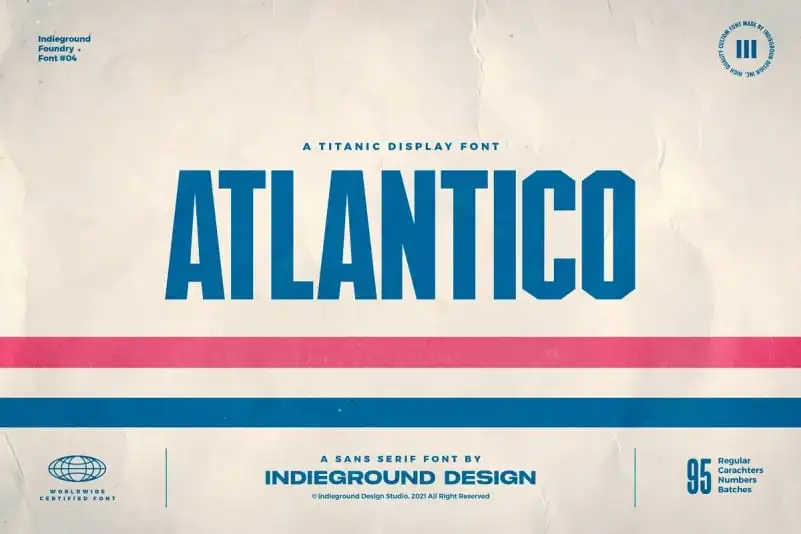
Atlantico Display Font – Download Grátis
A Atlantico Display Font é uma elegante fonte sans-serif inspirada nos fonts vintage, perfeitamente adaptada para estilos modernos e antigos. Este tipo de fonte foi criado pela Indieground Team com base nas características arredondadas e geométricas dos fonts antigos, mas oferecendo um toque moderno e limpo. Com design icônico e versátil, a Atlantico Display é perfeita para usar em títulos pesados de seus trabalhos artísticos. Seja para cartões de convite elegantes de casamento, embalagens de beleza ou moda, ela se encaixa perfeitamente nos projetos de design de livros, magazines e embalagens. Além disso, é uma fonte versátil que ajuda a destacar o estilo tanto retro quanto contemporâneo de seus trabalhos. Este pacote comercial inclui todos os caracteres mostrados no preview, permitindo-lhe expandir sua biblioteca de fonts para projetos diversos como marcas, identidades e branding. A Atlantico Display Font é uma ótima escolha para designers que desejam trazer um ar sofisticado e único aos seus trabalhos. Com o seu design simples e moderno, a fonte da Indieground oferece flexibilidade para adaptar sua estética em qualquer projeto, tornando-a a escolha perfeita para quem deseja um toque de elegância nos mais variados projetos.